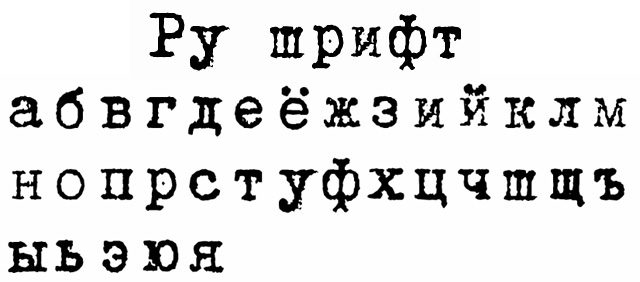
Шрифты для пишущих машинок , которые включают элементы старинных и нарисованных от руки надписей для объявлений, листовок и приглашений. Воссоздайте внешний вид старых документов с помощью шрифтов, воспроизводящих нажатия клавиш пишущей машинки, с неправильными штрихами и слегка кривыми буквами. Courier Font — моноширинный шрифт с засечками. Шрифт был разработан Говардом «Бад» Кеттлер (19 лет).19–1999). Первоначально созданный для пишущих машинок IBM, он был адаптирован для использования в качестве компьютерного шрифта, и его версии установлены на большинстве настольных компьютеров.
Astronaut Font
Astronaut Font — элегантный чистый шрифт с 6 стилями и многоязычной поддержкой. Это очень универсальный шрифт, который отлично работает как в больших, так и в маленьких размерах.
Шрифт для пишущей машинки Urania Piccola
Шрифт для пишущей машинки Triumph
Пишущая машинка Royal Vogue 1929 Шрифт